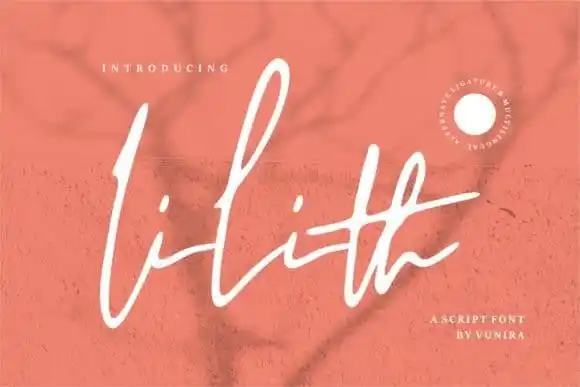
A Lilith Handwritten Font é uma elegante escolha para qualquer projeto que exija personalidade e charme. Desenvolvida pela 99designs, esta fonte foi criada pelo designer Vunira. A Lilith tem um toque delicado e fluido, combinando características clássicas com modernas de forma refinada. Este estilo é perfeito para logos memoráveis, marcas distintivas ou frases impactantes. Cada letra possui uma sensação única e encantadora que adicionará vida à sua arte digital. Esta fonte é ideal tanto para designers quanto para quem busca expressar a mão do artesão em suas criações digitais. Seja você criando um logotipo memorável, desenvolvendo uma marca inovadora ou simplesmente querendo inserir frases memoráveis em seus projetos de design gráfico, a Lilith Handwritten Font é uma escolha segura para que seu trabalho tenha um toque especial.